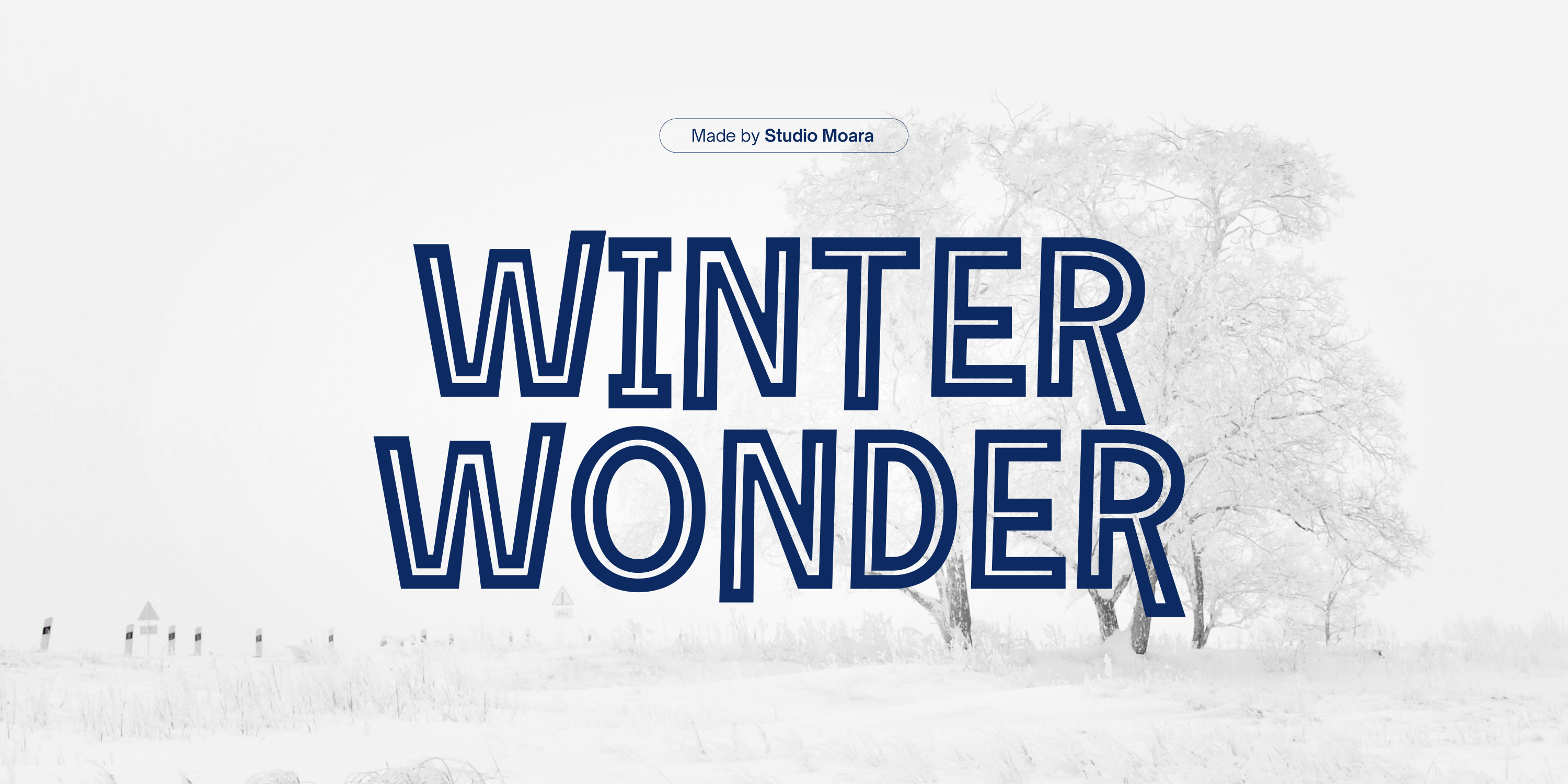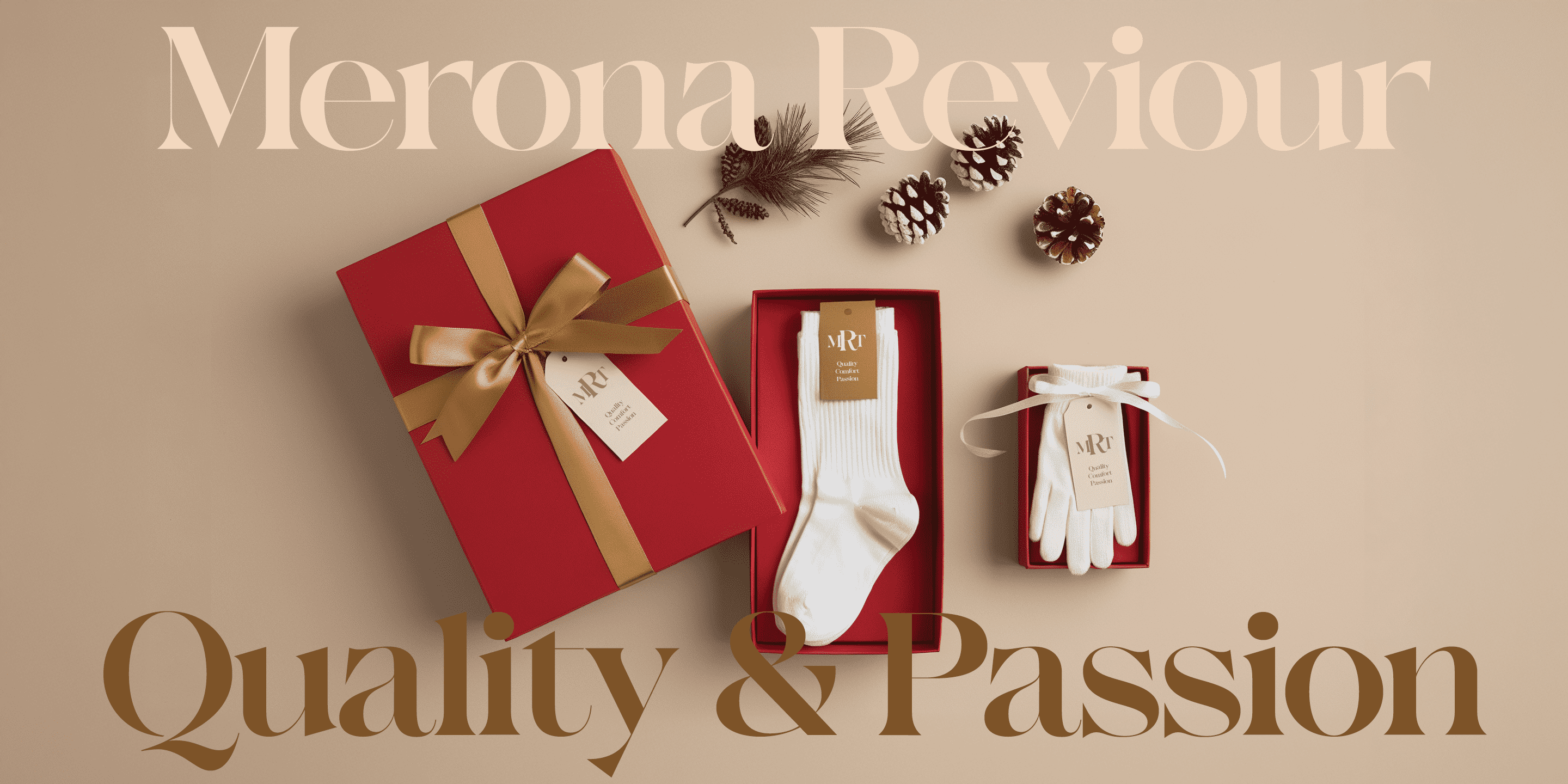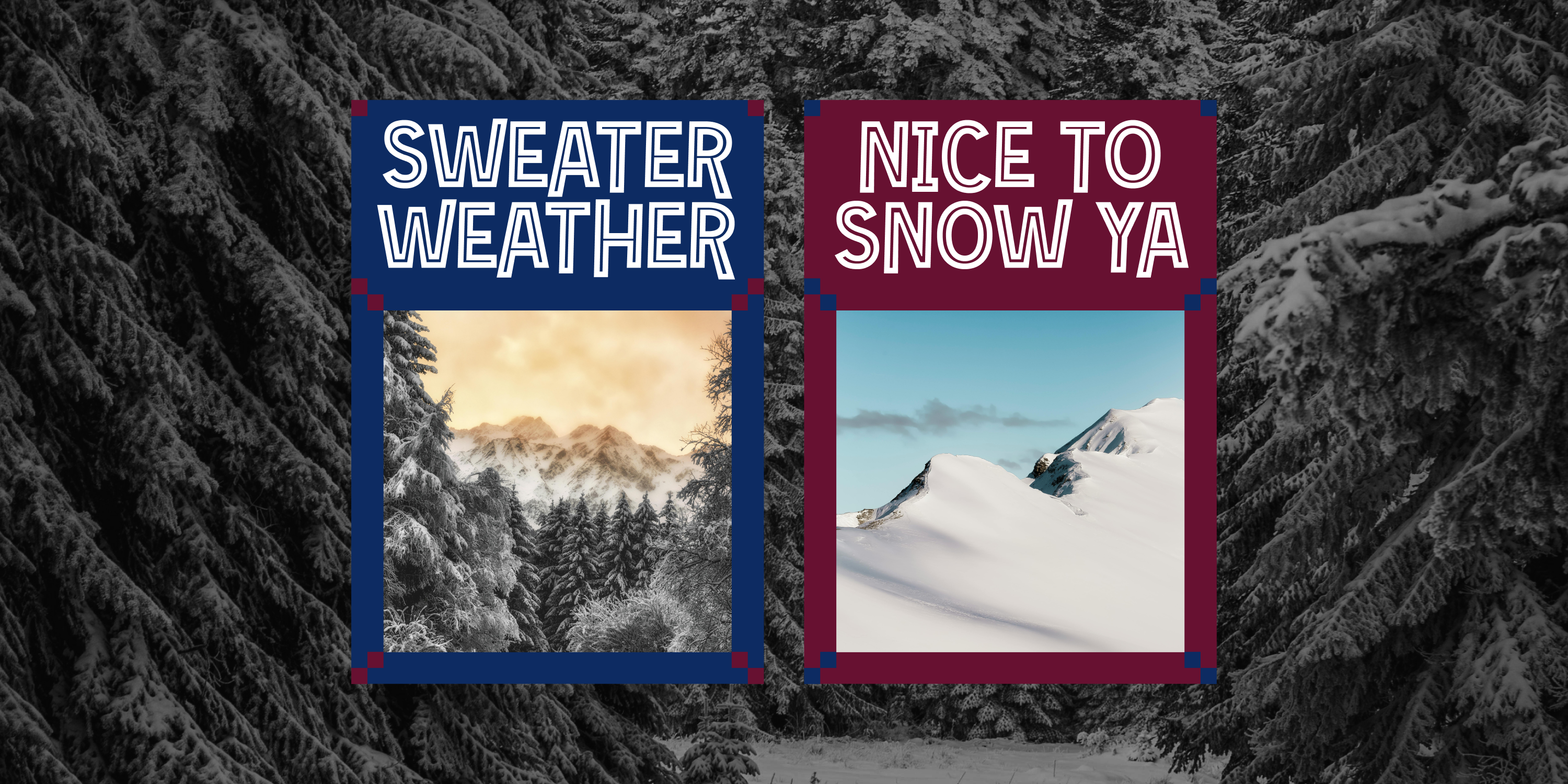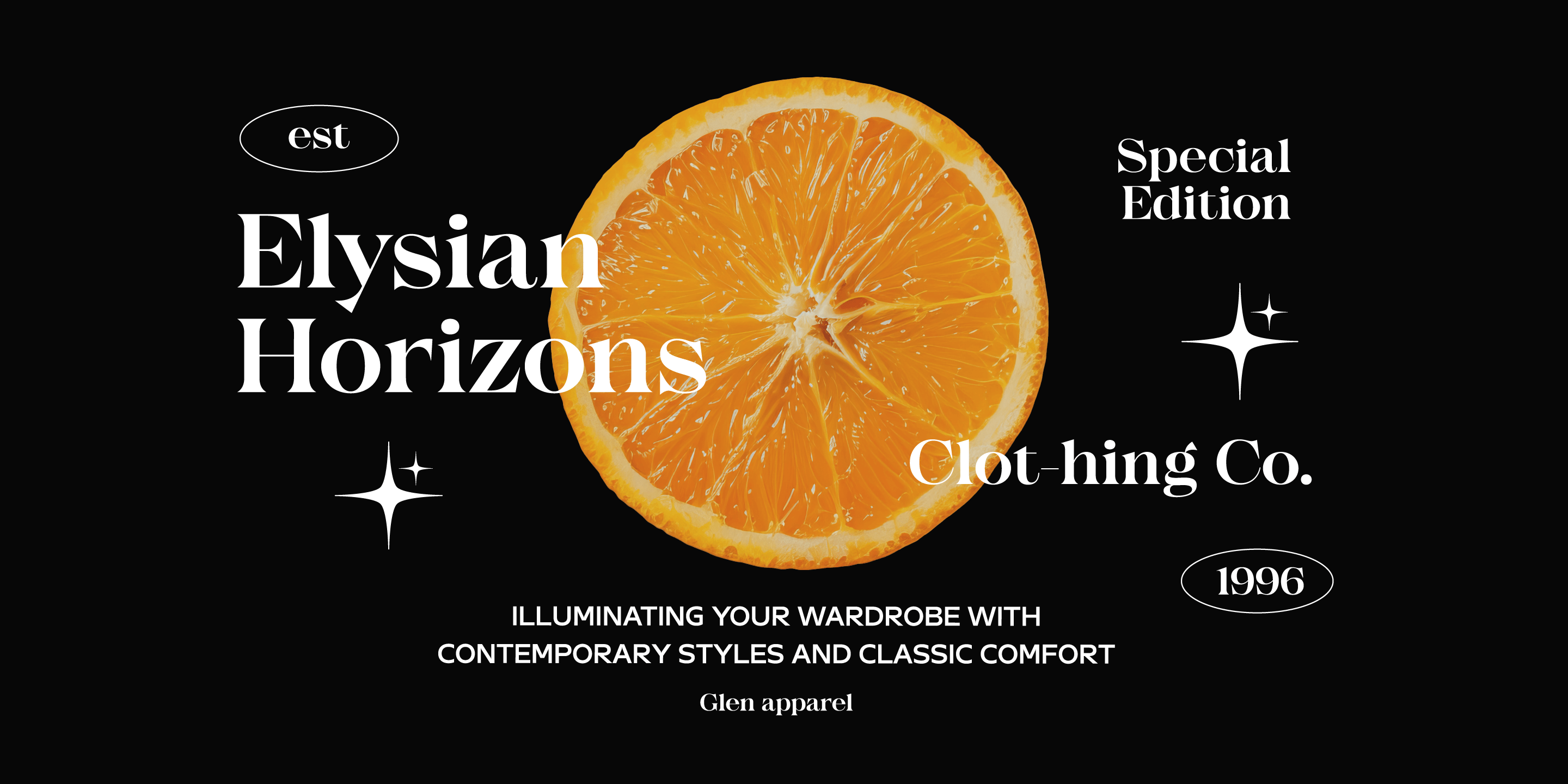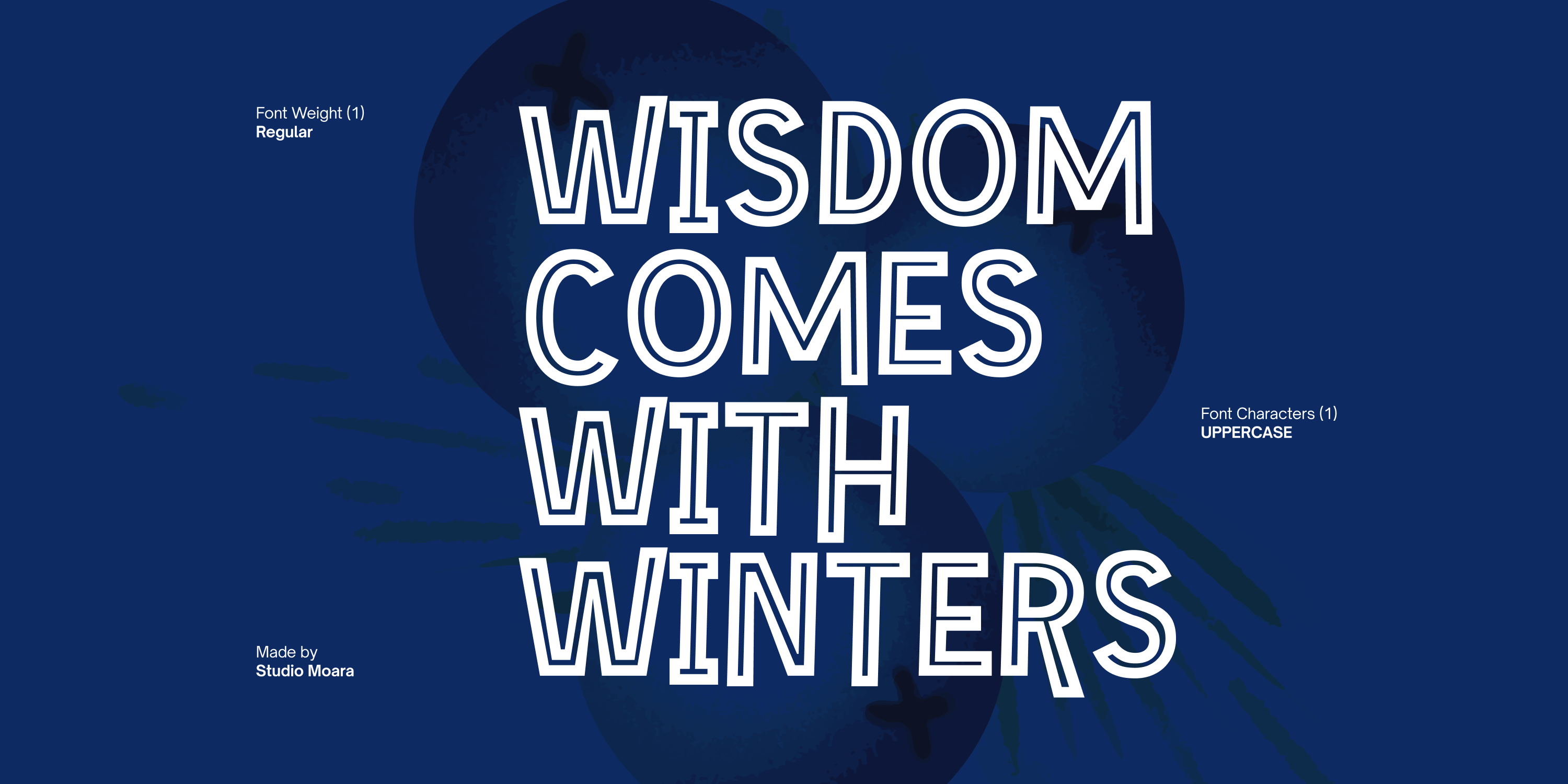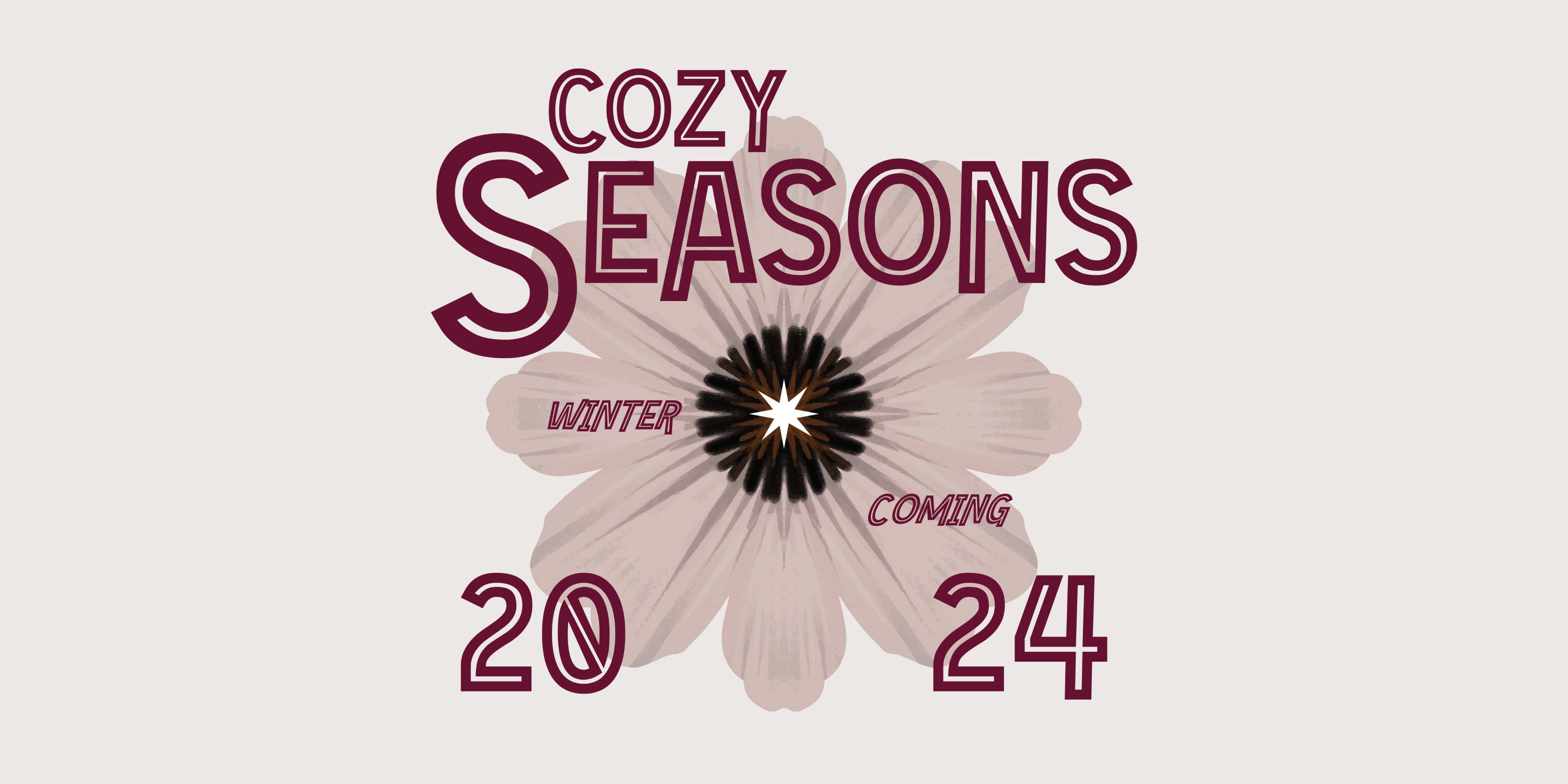
如果把初雪的轻盈、节日灯光的微暖,都凝成文字,会是什么模样?漫天雪花的安静铺陈、圣诞钟声的雀跃回响或许都能在字体的形状里找到回应。
随着大雪节气将至、圣诞冬意渐浓,我们精心挑选 8 款冬日氛围感字体,有的轻盈清爽如雪落无声,有的热烈活力如庆典欢歌。一同踏上这趟视觉旅程,让灵感在寒冬中滋长,随字体一同闪耀。
1|Winter Wonder
Foundry: Coasta
Designer: Panca Hasan
Winter Wonder 是一款充满圣诞气息的无衬线字体,能够为你的节日设计带来温暖的欢庆氛围。富有变化的镂空风格,兼具了干净利落的线条和轻松俏皮的视觉感受,形成迷人的节日特色。
无论你想营造冬日仙境般的氛围,或只是单纯传播圣诞的喜悦,Winter Wonder 都是赋予作品视觉美感的理想选择。
2|Tarita
Foundry: Pandeka Studio
Designer: Sagara Nararya
Tarita 是一款充满手作感和温暖气息的标题字体,灵动视觉搭配 44+ 创意替换字形,柔和曲线与俏皮笔触相融,让你的设计如同冬日里的烘焙甜品般温暖。
这款字体非常适合面包房、咖啡店、甜点铺、冬季节庆包装及菜单设计。自由组合字形,让你轻松打造独一无二的标识和品牌风格,为每个细节增添冬日手作魅力。
3|Magical Nordic
Foundry: Mans Greback
Designer: Mans Greback
Magical Nordic 的灵感源于宁静的北欧冬日传统氛围,是一款优雅现代的衬线体,线条纤细干净,粗细笔画与清晰轮廓形成对比,兼具经典与当代气质。
这款字体还带有微妙的魔幻感,完美契合圣诞节、冬季活动等季节主题设计。
4|Snowflakes
Foundry: Font Liner
Designer: Ghina Luthfiarieska
Snowflakes 是一款带有细致韵味的衬线字体,线条柔和、结构优雅,略带女性气质的笔触为设计增添温柔质感。
它拥有 Regular 与 Italic 两款样式,既能用正体展现轻盈的浪漫,也能通过斜体表达含蓄的精致。无论是品牌冬季主题活动、圣诞礼盒包装,还是节日贺卡的细腻问候,都能借这款字体找到恰如其分的表现方式。
5|Fastura
Foundry: Inviline
Designer: Virgiawan Listanto
Fastura 是一款流畅大胆的手写笔刷字体,在直接的视觉冲击力之外,也带有温暖的手作质感。
圆润的曲线与自信的笔触,又增添了不少适宜冬日氛围设计的温暖触感,使它非常适合品牌活动、海报设计、包装和贺卡等场景。
6|Dreamlight Winter
Foundry: Syauqi Studio
Designer: Muhammad Asroful Umam
带着冬日独有的浪漫气息,Dreamlight Winter 在纤细笔画中加入流畅弧度,笔画末端的卷曲又像是圣诞特有的彩灯装饰。它没有刻意强调节日元素,却天然带着年末时节的温柔闪光。
无论应用的设计场景如何,它都能轻松切换于古典与时尚之间,让版面呈现出轻盈高级的气质。在需要表达温暖、浪漫、静谧时,它会是那个恰到好处的选择。
7|The Snowday
Foundry: Sronstudio
Designer: Muhamad Yusron Billah
The Snowday 有着手写般的随性笔触,就像在雪地上用树枝涂鸦留下的轻松印记。它不追求规整,反而用一点点凌乱与童趣,把冬天的欢乐氛围烘托得刚刚好。
字体线条圆润温和,读起来像是一声温暖的问候,非常适合包装、标签、手作品牌与节日礼物等应用。
8|Winterhold Kingdom
Foundry: Timurtype
Designer: Wara Sigit Tri Pamungkas
Winterhold Kingdom 是一款充满灵动意趣的手写字体,基于现代书法的灵感,呈现优雅时尚的冬日魅力。
流动自然的笔触与疏密有致的书写节奏,让它非常适合品牌设计、邀请函、社交媒体视觉与任何需要精致手写风格的创意项目。
"title": "雪落字体间:8 款冬季氛围设计必备字体特辑"